Aún con el buen sabor de boca que nos dejó el 7 CIT, os queremos contar como transcurrió. En un nuevo formato más íntimo y personal y con las comunicaciones como centro del evento, la temática fue la tipografía pública. A diferencia de años anteriores se estrenaron nuevos espacios como el TypeCrit (revisión de tipos por mano de expertos) y las mesas de trabajo, aunque no hubo mercadillo tipográfico y el ChiliType (espacio de micro-exposiciones) pasó a convertirse en un rincón de relax.
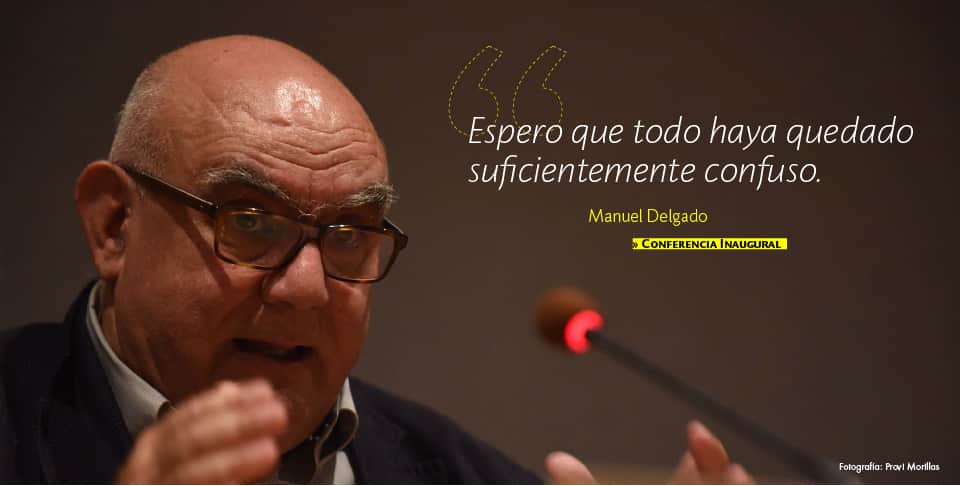
Arrancamos el congreso en EASD (Escola d’Art i Superior de Disseny de València) con con una interesante reflexión de Manuel Delgado sobre espacio público en la que remarcó la diferencia entre lo público entendido como la propiedad privada del estado y lo público como aquello que está al alcance de todos, un espacio con exposición a la visión ajena, que está “fuera”, ligado al concepto de “salir”, donde la vida es impredecible porque los principios de interacción se van construyendo sobre la marcha. Y, en este sentido, remarcó la diferencia de éste concepto de lo público, frente a una ilusión de un orden público entendido a partir de la falsa idea de igualdad (que afirma ser inexistente) entre individuos que conforman un estado.
COMUNICACIONES
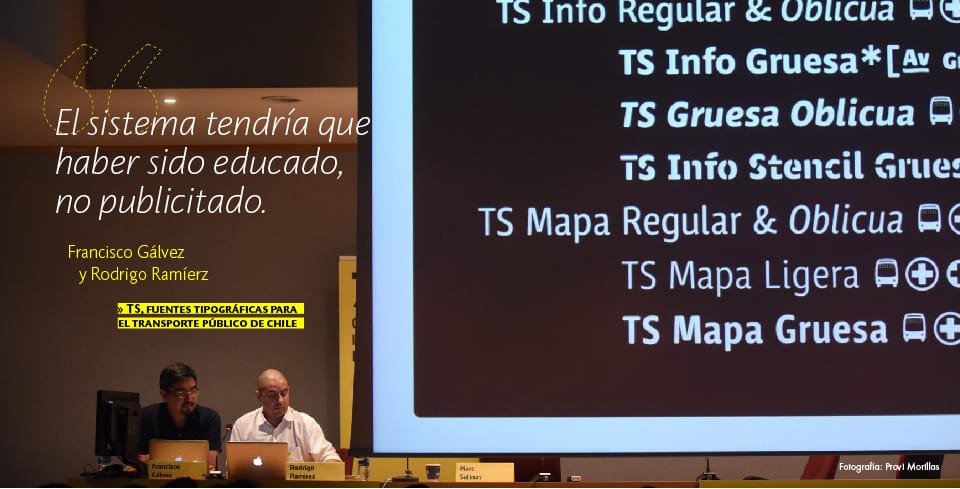
Francisco Gálvez y Rodrigo Ramírez nos presentaron el nuevo estándar de transporte público de Santiago de Chile, la tipografía TS (TranSantiago), un arduo y largo proceso que partía de la inexistencia absoluta de una coherencia en una ciudad de seis millones de habitantes. El encargo, que pedía un estándar universal e internacionalidad, se extendió en sus distintas fases en un período de más de una década. Aparte del proceso y las interesantes soluciones técnicas, como los vértices redondeados para prevenir el vandalismo en los vinilos, todo un sistema de pictogramas y un sinfín de abreviaturas accesibles a través del OpenType; nos sorprendió su traumática implementación que fue concebida como “la peor política pública desde el fin de la dictadura”, la reflexión fue que este nuevo sistema debería haber sido acompañado de un proceso formativo más que de una gran campaña publicitaria.
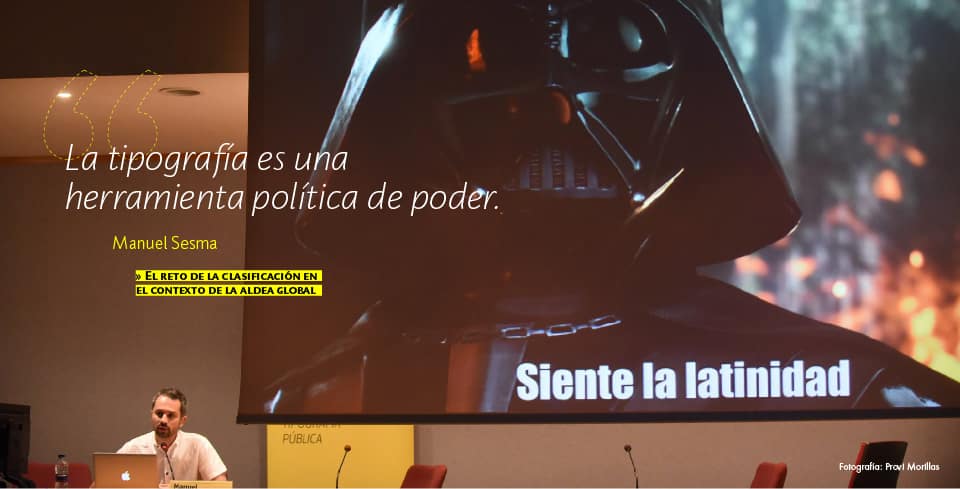
Manuel Sesma se encargó de ocupar la hora de Éloïsa Pérez que no pudo llegar por un problema en el aeropuerto. Sesma plantea la tipografía como herramienta política y afirma que toda clasificación es una imposición ideológica analizando las dinámicas del poder. Por ello, critica la persistencia de la clasificación Vox-ATypI como etnocentrista y discriminatoria y apela a la eliminación de la latinización. Propone una clasificación que sea flexible y mutable, concebida desde el “nosotros” y que rompa con la hegemonía, no obstante sin proponer alternativas y oponiéndose a cualquiera de las existentes con un rotundo ¡No!
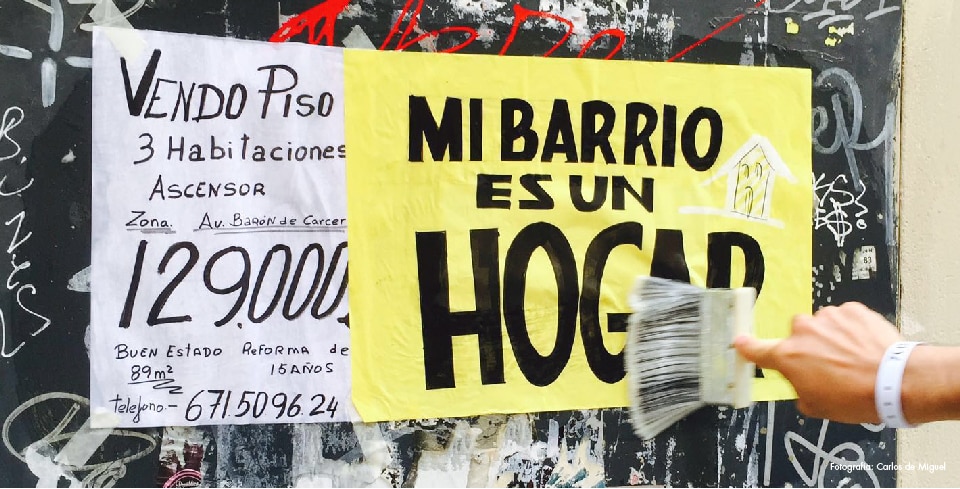
En el descanso para comer pudimos aprovechar para observar por las calles de Velluters el resultado del taller de tipografía como herramienta activista en el espacio público impartido por Un Mundo Feliz y Chulotype. Un ejercicio de inmersión en el barrio a través de carteles realizados a mano que interactúan, divierten y comunican.
Sustituimos la hora de la siesta por las comunicaciones entorno a la multiculturalidad y el valor identitario de la lengua.
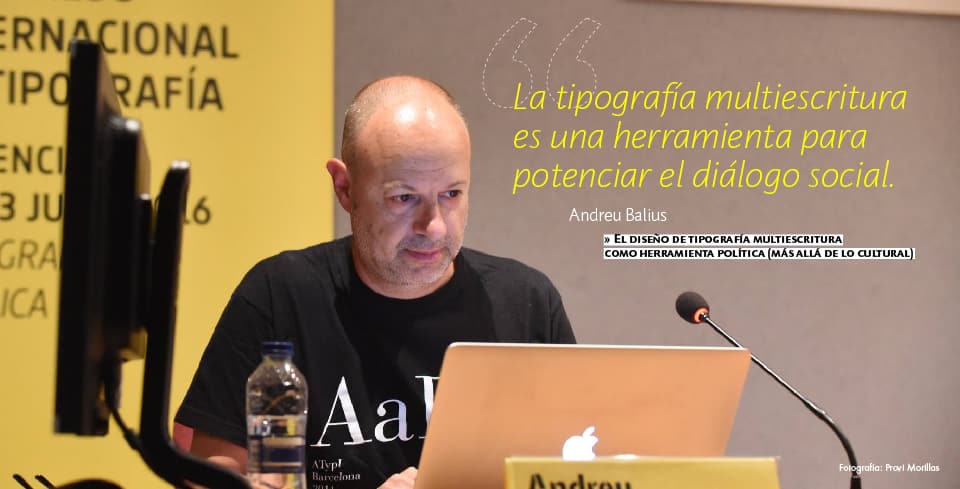
Andreu Balius después de haber analizado cómo la tipografía ha funcionado como herramienta política a lo largo de la historia, nos habló sobre la relación entre multiculturalidad y multiescritura (con ejemplos de latin-árabe) presentándonos diferentes proyectos reales que trabajan el acercamiento de grupos diferentes o incluso enfrentados. Afirma que el interés por la coexistencia de culturas en una sociedad global es el compromiso actual con lo público, asumir los valores culturales y sociales y tomar conciencia de la tipografía como herramienta de transformación, siempre desde la necesidad de una voluntad política que busca fomentar el diálogo y una convivencia desde el respeto.
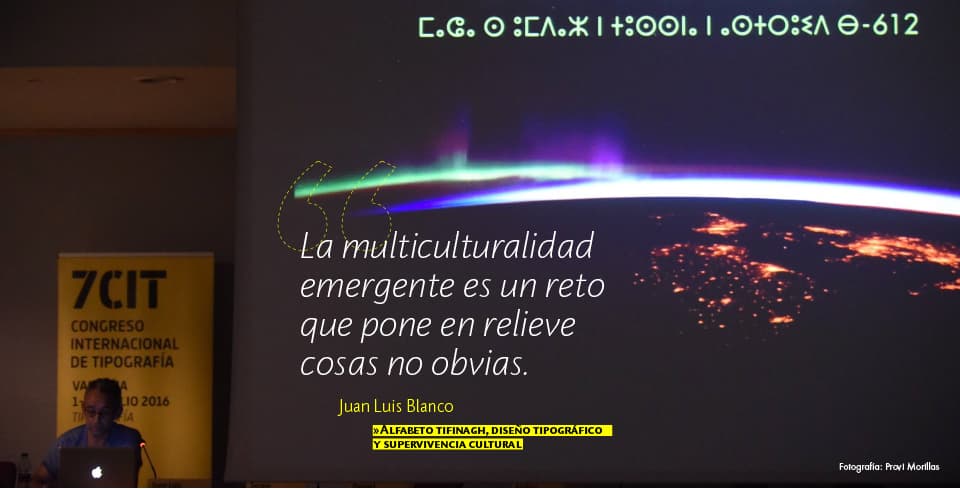
La investigación de Juan Luis Blanco estudia a nivel tipográfico la escritura Tifinagh, escritura propia del idioma Amazigh que se hizo oficial en Marruecos en 2011 y que puede ser escrito en otras dos escrituras (latin y árabe). Con la decisión de normalizar la lengua Amazigh con su propio alfabeto Tifinagh sin apenas documentación histórica, puso sobre relieve una serie de cuestiones por resolver. Una fue le inexistencia de minúsculas, las dificultades de lectura derivados, así como los problemas de escritura. Finalmente estudió la creación de una cursiva del Tifinagh a partir de un proceso participativo que tomó como modelo de partida la evolución de la escritura latina. En este sentido la multiculturalidad como reto emergente pone en relieve cosas no obvias, como la necesidad de apoyarse en sistemas conocidos para resolver nuevos problemas o la realidad de contextos inversos (tres escrituras para un mismo idioma a diferencia de una escritura para multitud de idiomas como pasa con la escritura latina).
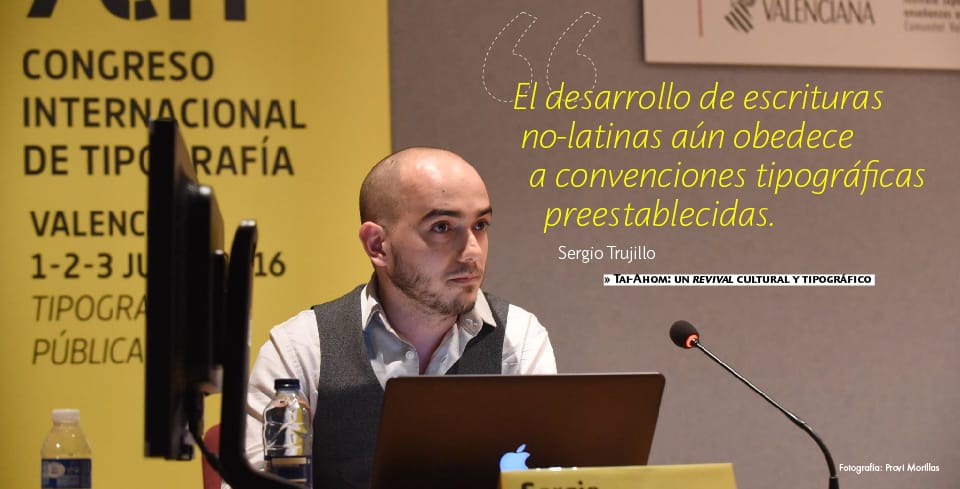
Sergio Trujillo nos presentó una tipografía desarrollada para el idioma Tai-Ahom del estado Assam (India) caído en desuso después de la ocupación británica y que sólo sobrevivió en manuscritos y rituales religiosos. En un contexto de revival Trujillo se enfrenta a problemas no resueltos desde la perspectiva tipográfica como el repertorio de caracteres, sus dimensiones y posicionamiento y el encaje de las vocales que se enlazan de una forma inusual para nosotros. De este modo su trabajo ayuda a establecer un marco base para futuros diseñadores e investigadores, no solo para el desarrollo tipográfico del Tai-Ahom sino también para otras tipografías no latinas de un carácter similar.
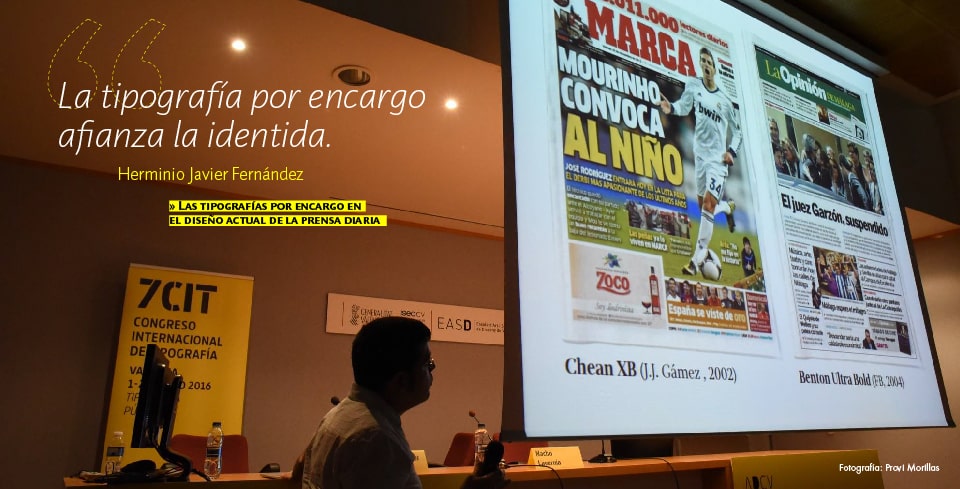
Herminio Fernández nos invitó a un paseo por el rediseño tipográfico de diarios españoles desde finales del siglo XX impulsado especialmente con la creación de Majerit de Mario Feliciano en 2007 para El País, que ayudó a asentar la tipografía como vehículo diferenciador e identitario dentro del espectro plural y diverso de la oferta de prensa. No obstante las tipografías de venta general y las adaptadas son el modelo más usual, a excepción de ABC, El País y la Voz de Galicia que cuentan con sus propias tipografías corporativas. También nuestra tipografía Futura estuvo presente en esta comunicación con su versión adaptada para USA Today.
Homenaje
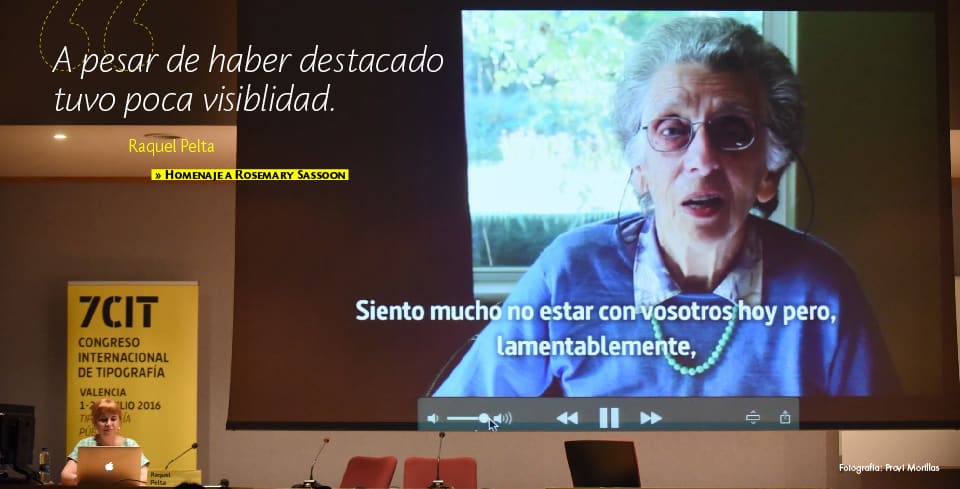
Tras estas comunicaciones, Raquel Pelta hizo un especial Homenaje a Rosemary Sassoon, nos presentó una sobresaliente figura desconocida a pesar de haber destacado con sus investigaciones sobre la escritura. Su amor era el lettering y llevó siempre una vida paralela entre sus tareas como ama de casa y su vida profesional y académica. Obtuvo el título de doctora en la Universidad de Reading además de haber publicado más de una decena de libros. Sus esfuerzos se centraron en la escritura y su enseñanza, no sólo a nivel educativo, sino también a nivel médico. Desarrolló Sassoon Primary junto a Adrian Williams, una tipografía de lectura especialmente concebida para niños. Sassoon hoy tiene 85 años, vive en Australia y un reciente percance le impidió asistir al Congreso aunque nos dedicó un vídeo con un artículo que reflexiona acerca del diseño tipográfico para determinados lectores especiales.
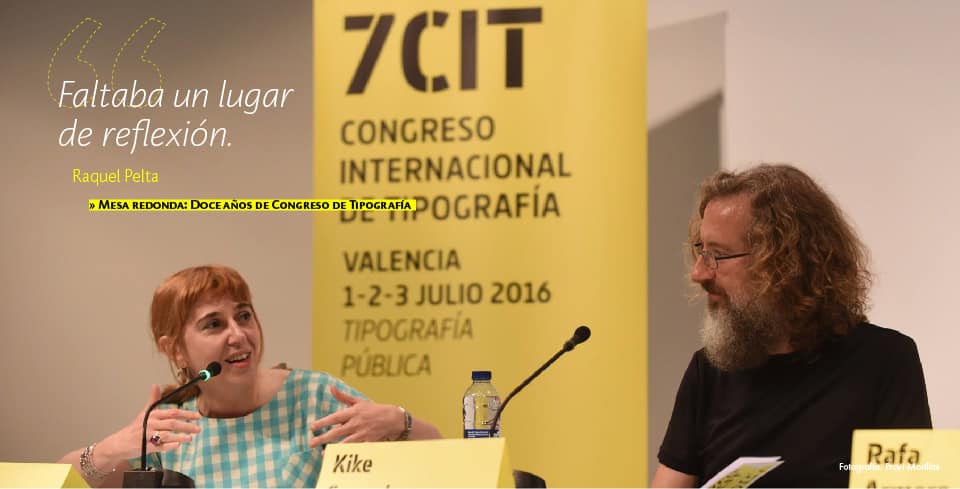
Mesa Redonda
Problemas técnicos en el Museo valenciano de la ilustración y la modernidad (MuVIM) obligaron a postponer Cuarto de Tipo y se dio paso directo a la mesa redonda sobre los Doce años de Congreso de Tipografía. Analizando el contexto de su aparición, se recordó que cuando nació no existía ningún evento de este tipo pero que a día de hoy existen muchos eventos de discusión, reflexión y creación sobre el mundo tipográfico. Raquel Pelta expresó sus recurrentes dudas sobre la necesidad de dar continuidad al encuentro. Por este mismo motivo hubo un intencionado planteamiento de reducir este año el marco del congreso (siendo más congreso y menos festival) y centrarlo en la investigación, pero lamentando con desánimo el retraso y la limitación en la parte académica y de investigación en España. La conclusión en la que todos coincidieron fue que el logro del congreso residía, no en lo que era a día de hoy sino en todo su recorrido.
El segundo día comenzamos debatiendo distintos temas en las diferentes Mesas de Trabajo, otra gran novedad del Congreso, cuyas conclusiones (más que interesantes) os contaremos en un próximo post.
Cuarto de tipo
Después pudimos ver las ansiadas comunicaciones que teníamos pendientes del día anterior en Cuarto de Tipo.
Nuria López nos presentó un proyecto impulsado a partir de un planteamiento personal: ¿Si el diseño es la gente [como afirma Jane Jaco], para qué existen entonces los diseñadores?”. Blind Words combina el braille con las letras gráficas construyéndolas a partir de una retícula derivada del sistema de escritura para ciegos.
Carlos del Toro presentó su tipografía Recia realizada bajo el encargo de The Indian Type Foundry que tuvo que dar respuestas a dos exigencias especiales: una buena legibilidad a tamaño pequeño y un buen resultado en impresión en offset tradicional. Para el autor un apasionante reto en el que enfrentarse a la realidad y aprender de las diferencias culturales, otras visiones, de las críticas y del cliente que siempre tiene la razón.
El Colectivo Llotja de la ESDA Llotja de Barcelona nos presentó su proyecto Tipografías del 240 aniversario de la Llotja para el que se realizó un estudio de las obras gráficas de artistas célebres que pasaron por ella. El reto consistía en realizar una reinterpretación actual de estas letras y encontrarle un sentido contemporáneo al uso de la impresión tradicional. Esta combinación de la tecnología digital con los procesos artesanos crea nuevas posibilidades y nos presentan un resultado experimental, moderno y creativo que incluso da pie a su continuación por parte de futuros alumnos. Uno de sus participantes fue el ganador del Premio Paco Bascuñán… ¡Enhorabuena, Matias Fosco Tornielli!
¡Extra, Extra!
Más tarde llegaban las últimas novedades en cuanto a aplicaciones y plataformas digitales
Una presentación en un spanglish de lo más divertido para mostrarnos todo el potencial de las novedades que incorpora la última versión de Glyphsapp.
El simpático trío andaluz que componen Fontown nos presentó una herramienta que por fin plantea una solución al uso tipográfico para estudiantes a través de una plataforma que ofrece licencias especiales e incorporando además un novedoso filtro de búsqueda. Una solución fácil y flexible en la que se nota el mimo y la prioridad con la que se ha trabajado sobre la experiencia de usuario.
Y finalmente, nuestros amigos de Chulotype aka Typomad, además de echar una agradecida mano en la organización nos contaron que muy pronto estrenarán una nueva web que servirá de punto de encuentro y gran referente del mundo tipográfico tratando temas de opinión, investigación, entrevistas, eventos, vídeos, reseñas de tipo y actualidad. ¡Estamos deseando que la publiquen!
EMERGENTES
Noe Blanco hizo de la hora del café, una sobremesa más que interesante. Nos habló de cómo encontró su hueco en el mundo tipográfico especializándose en el hinting (proceso causante de malestar con su simple pronunciación, como nos comentaba) y convirtiéndose junto a Joan Carles Casasín en uno de los dos españoles especialistas en producción. Después de contarnos su último proyecto tipográfico realizado para Wallapop junto a Íñigo Jeréz, nos recordó que “a todos nos gusta diseñar letras” y por supuesto a ella también. Estamos deseosos que encuentre pronto el hueco para terminar su tipografía Mínima (que hace dos años ya nos presentó en Cuarto de Tipo), seguro que en su nueva casa campestre consigue encontrar el tiempo que necesita para sacarla a la luz. ¡Ánimo, Noe!
Después uno de los discípulos de Iván Castro y Oriol Miró, Joan Quirós, nos deleito presentándonos sus trabajos destacados y haciendo un recorrido por su biografía profesional que tiene sus orígenes en el graffitti, la calle y las portadas de discos hardcoretas. Viéndose obligado a abrirse camino por su propia cuenta, montó un estudio junto a sus compañeros de la escuela que llamaron Voltio. Pudimos ver sus primeros intentos caligráficos fallidos y dispersos pero que obtuvieron un nuevo impulso al conocer en un taller a sus maestros ya mencionados. La práctica de la caligrafía se convirtió desde entonces en una placentera obsesión. Y concluye que el hilo conductor de su vida, el placer por el diseño de letras y la escritura, cierra el círculo convirtiendo pasión en profesión.
Más tarde continuamos con los invitados internacionales hablándonos de tipografía no comercial con una función mucho más allá de lo económico.
HUDA SMITSHUIJZEN ABIFARÈS
Nacida en Beirut y residente en Amsterdam, nos contó acerca de su fundación Khatt enfocada a la tipografía árabe y el estudio del diseño en las regiones geográficas que la usan. Typographic matchmaking es un proyecto que cuenta con varias ediciones juntando a múltiples equipos de diseñadores tipográficos de escritura latina y árabe para trabajar en la creación de tipografías multiescritura, que cobran vida también en aplicaciones urbanísticas y en tres dimensiones. La aspiración va más allá de lo formal: El aprendizaje mutuo, crear y hacer cosas de forma novedosas, enfrentarse a problemáticas desconocidas y finalmente presentar un resultado tangible tiene como fin el acercamiento de culturas y por lo tanto tener un impacto en la sociedad, facilitar la convivencia, el entendimiento mutuo y el acercamiento, como también reforzar la identidad cultural. Los resultados de estos trabajos que en cada edición se recogen en un libro son sorprendentes y los avances la última edición nos dejaron con la boca abierta.
RUEDI BAUR
El invitado estrella de esta edición nos habló acerca del diseño cívico en espacios comunes y urbanos con la pretensión de recuperar un diseño al servicio de la gente o, más concretamente, de los ciudadanos. A través de una serie de ejemplos de posibles formas de actuar en este sentido, Ruedi nos mostró casos reales de diseño multidisciplinar en el que la comunidad es partícipe del proceso. Sus proyectos ligados a los sistemas de identificación y orientación buscan dar respuestas a miedos y la desorientación en un contexto dominado por un imperativo comercial. Identifica el branding como una catástrofe propia de un contexto social de superficialidad y dominado por la propaganda. Por ello reivindica un diseño crítico y autocrítico que ayude a mejorar la calidad de vida de las personas, que ayude a comprender y representar un mundo complejo huyendo de la simplificación, con el derecho a incorporar elementos inútiles en la ciudad y la intervención participativa en los procesos. El diseñador como abogado de los ciudadanos y en cooperación transdisciplinar tiene la capacidad, afirma Ruedi, de transformar los espacios y las comunidades abriendo el diálogo y mostrando la belleza de la pluralidad y las diferencias.
ANN BESSEMANS
La investigación de Bessemans culmina en el diseño de una tipografía como solución tangible. Ella estudió los parámetros tipográficos de heterogeneidad y homogeneidad para detectar cuáles eran aquellos que mejor podían leer los alumnos con dificultades de visión durante el proceso de aprendizaje de la lectura. Para ello realizó un estudio con niños que para ellos llamó “El juego de las palabras“. Con las conclusiones de este estudio como premisa, diseñó la tipografía Matilda aplicando los parámetros que mejor sirvieron a los niños con baja visión, siendo estos principalmente el ritmo y la dirección. Matilda es una tipografía con serifas asimétricas (convexos y cóncavos), formas amplias y abiertas, letras redondas, eje vertical y ascendientes y descendientes largos. Su intención es nuevamente someter a estudio esta tipografía para confirmar su aptitud para el propósito que fue creada.
COMUNICACIONES
El inicio de la última jornada se vistió de activismo.
El humor es una herramienta indispensable para el colectivo Un mundo feliz (Gabriel Martínez y Sonia Díaz) que se definen ciudadanos antes que diseñadores. A diferencia del activismo francés con un gran predominio de la palabra, su lenguaje es más icónico, mejor entendido en España. Su impulso es ético e idealista y defienden un diseño al servicio del interés público y no de las marcas. Sus intervenciones tienen como objetivo generar otra forma de pensar o al menos invitar a la reflexión y cambiar la forma de percibir. Una pareja implicada y volcada en algo que les gusta para propulsar la idea del diseñador con opinión, la subversión, la desobediencia no violenta, el constructivismo, la solidaridad y la sostenibilidad emocional, poniendo a disposición el lenguaje activista creado por ellos mismos (que califican como diseño fallido o esbozos) para que los demás lo puedan usar.
Uqui Permui nos habló de la letra feminista en la calle analizando las preferencias gráficas por estos colectivos activistas constatando dos vertientes principales: la preferencia por tipografías bold de palo seco tanto en gráfica de difusión (como hacía Barbara Kruger con Futura) como en aplicaciones stencil de calle o incluso en el propio cuerpo (como Femen) por un lado, y las composiciones caligráficas de letras enlazadas en minúsculas, por otro. Éste último dota a los grupos que lo emplean (siendo el colectivo mejicano Polvo de gallina negra y el boliviano Mujeres creando los dos ejemplos presentados) una fuerte identidad que les define y hace reconocibles. Finalmente nos presentó una campaña contra la violencia machista que diseñó en su estudio y que fue encargada por el Ayuntamiento de Santiago de Compostela. Poniendo los recursos y la gráfica al alcance de todos, no sólo los establecimientos implicados la emplearon, sino al público en general que de forma inesperada se apropió de esta campaña. Los ciudadanos la hicieron suya y esto fue la prueba de su éxito. Así la campaña dio respuesta a la reivindicación feminista, paradójicamente perdiendo el carácter subversivo al ser impulsado desde las instituciones y apoyado por los comercios.
Y de la política local nos trasladamos a proyectos tipográficos gubernamentales en América Latina. Amanda Lemus puso de manifiesto, mediante un análisis de dos tipografías corporativas estatales de México, la relación de la ideología con el valor metafórico de las formas de las letras. Mostró que podemos encontrar los valores e ideas de los gobiernos, reflejados no solo en las formas tipográficas que dan voz a estas ideas, sino también en el modo de implementación o en la forma de nombrarlas. De este modo la tipografía Presidencia encargado por el gobierno de Felipe Calderón refleja con su carácter anguloso y sus construcciones robustas una apariencia firme y poco flexible. Su inspiración en la cultura tolteca evidencia un espíritu militarizado. El reflejo de un gobierno autoritario con una política dura y frontal que impone sus propias reglas incluso sustituyendo la nomenclatura de los distintos estilos. Por otro lado, Soberna, encargada por el gobierno de Enrique Peña Nieto pone de manifiesto, ya en la elección de su nombre, una clara intención: el reflejo de una institución de máximo poder. Sus formas de incisas romanas recuerdan a la voz de un imperio centrista, anclado en el orden del pasado traicionando la promesa de renovación a pesar de buscar reflejar un espíritu moderno con formas de sobriedad y formalidad.
A diferencia de los anteriores ejemplos, Pedro Álvarez y Rodrigo Ramirez nos presentaron una tipografía corporativa gubernamental que logró trascender y sobrevivir a las barreras ideológicas de gobiernos opuestos. Después de ver la evolución política e histórica en Chile, vimos el diseño del sistema tipográfico GobCL sucedió a un nefasto intento de implementar en un contexto político inadecuado una nueva identidad institucional. Coincidiendo el cambio de gobierno con el traumático terremoto de 2010, a tan sólo 13 días de esta tragedia el gobierno de Sebastián Pïñera consideró prioritario este cambio corporativo que fue contestado con un vehemente rechazo por parte de la sociedad chilena. El desarrollo de una la nueva identidad y GobCL que sustituiría a la identidad que el gobierno finalmente calificó como “transicional” logró mediante un carácter más bien neutro y simple, descalificado por la oposición política como “poco innovadora” y hasta “aburrida”, crear un “letra de gobierno”, asociada a lo público y al alcance de todos mediante descarga gratuita. La aceptación y su consistencia logran que la tipografía trascienda y aún a día de hoy el gobierno de Michelle Bachelette mantenga la misma tipografía e imagen corporativa.
Nos encantó poder disfrutar de la exposición de Éloïsa Pérez a pesar de sus dificultades para llegar a Valencia, ya que mostró cómo la investigación teórica puede culminar en una aplicación práctica útil a la par que estética. En su estudio sobre cómo se enseña a escribir en Francia constata que no existe ninguna normalización y se cuestiona la idoneidad de los numerosos modelos empleados y la dicotomía entre modelos de lectura y escritura, llegando a la conclusión de que desligar el sentido figurativo de la forma de la letra resultaría útil a los niños en el aprendizaje de la escritura. El modelo que propone hace una descomposición de las letras y acerca de una forma extremadamente lúdica las formas básicas que componen las letras a los niños no alfabetizados. Su modelo ya se está testando con la intención de implementar una normalización a nivel estatal.
Hasta la próxima
Empapados de letras, tipografías y una buena dosis de inspiración, Raquel Pelta pasó a despedirse del congreso. No es casualidad que un congreso centrado en el diseño al servicio de todos y que cuestiona nuestro papel en el conjunto de sociedad, cierre este ciclo de doce años de congreso dirigido por ella. Como siempre, este punto de encuentro tipográfico internacional ha sembrado nuevas ideas, ha acercado a personas y ha impulsado la participación en la construcción de nuestro futuro. Nos despedimos con un enorme ¡Gracias! a todos que lo hacen y han hecho posible. Y en esta ocasión especialmente a Raquel, ¡te deseamos todo lo mejor!